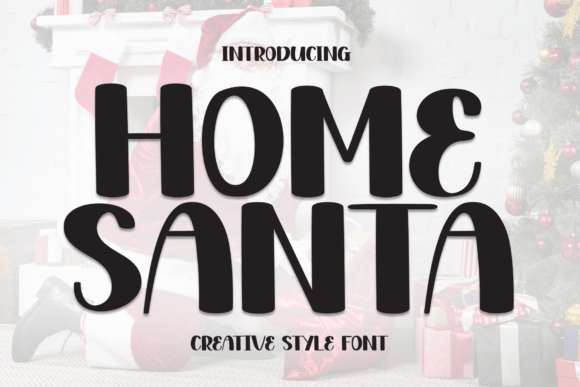
Home Santa Font
Home Santa Font – خط هوم سانتا
أضف لمسة سحرية دافئة إلى تصاميمك مع Home Santa Font، الخط المثالي لموسم الأعياد والاحتفالات! يتميز هذا الخط بأسلوبه الأنيق والمبهج، مما يجعله مثاليًا لتصميم بطاقات التهنئة، الشعارات، الدعوات، منشورات وسائل التواصل الاجتماعي، والمزيد.
✨ المميزات:
✅ تصميم فريد مستوحى من أجواء الكريسماس والدفء العائلي
✅ يدعم الحروف الكبيرة والصغيرة لتوفير مرونة في الاستخدام
✅ مناسب لمختلف الاستخدامات، من الطباعة إلى التصميم الرقمي